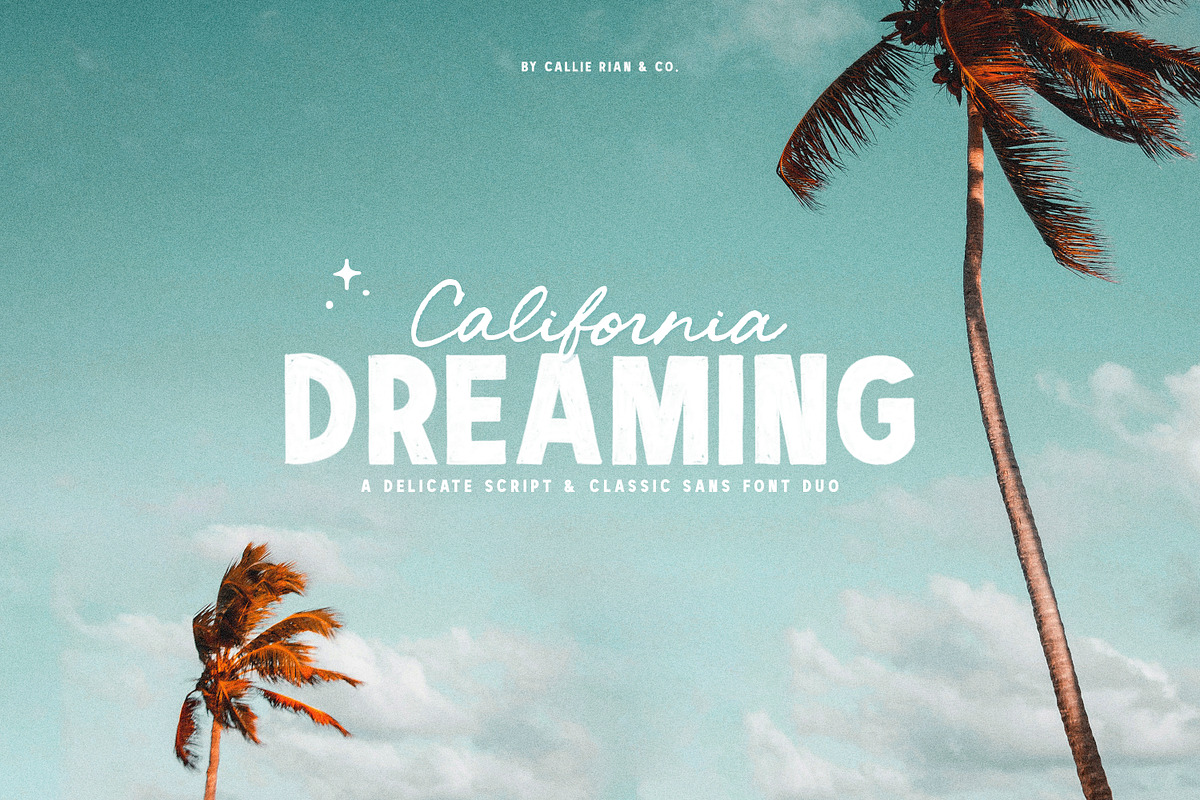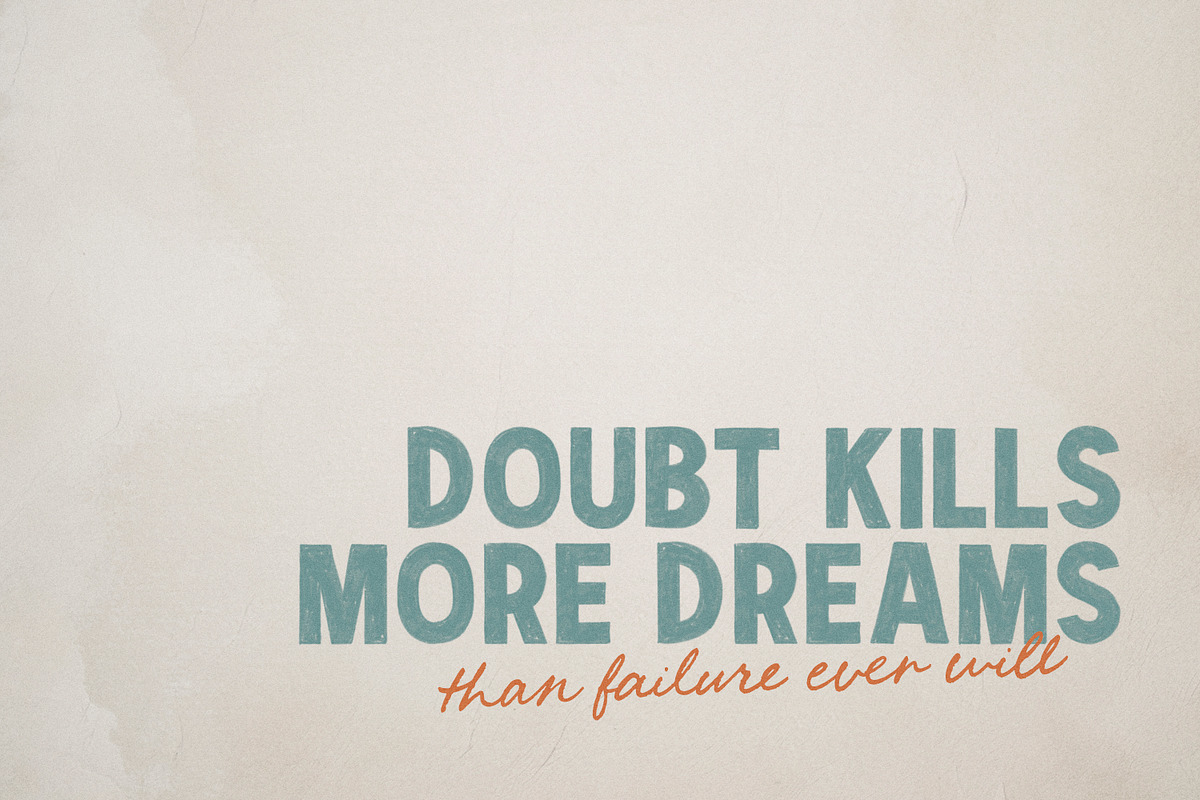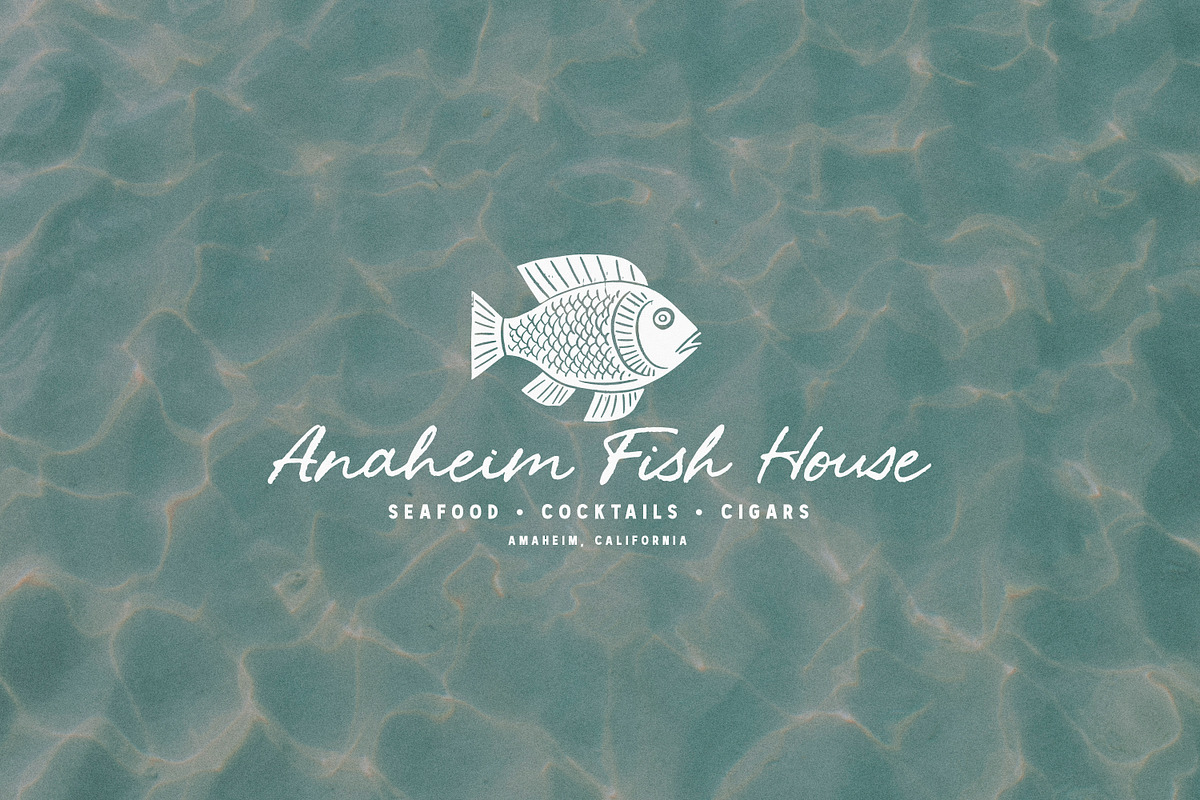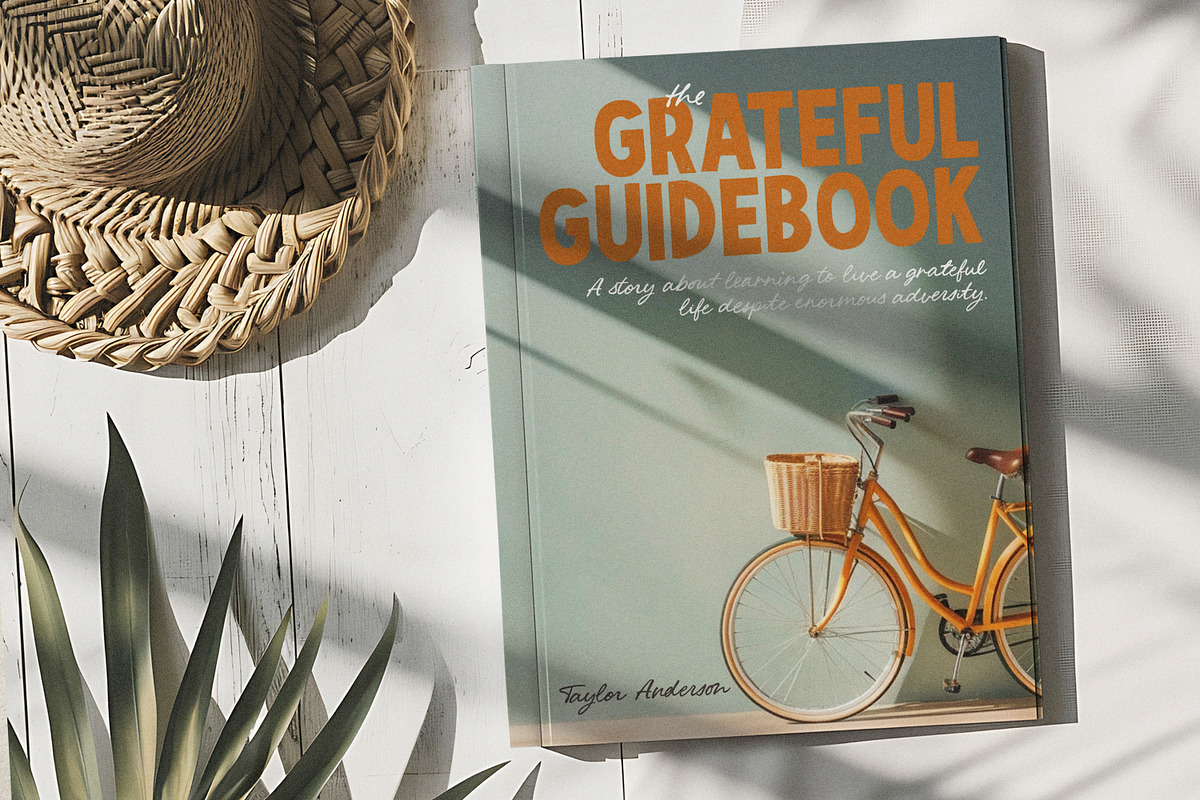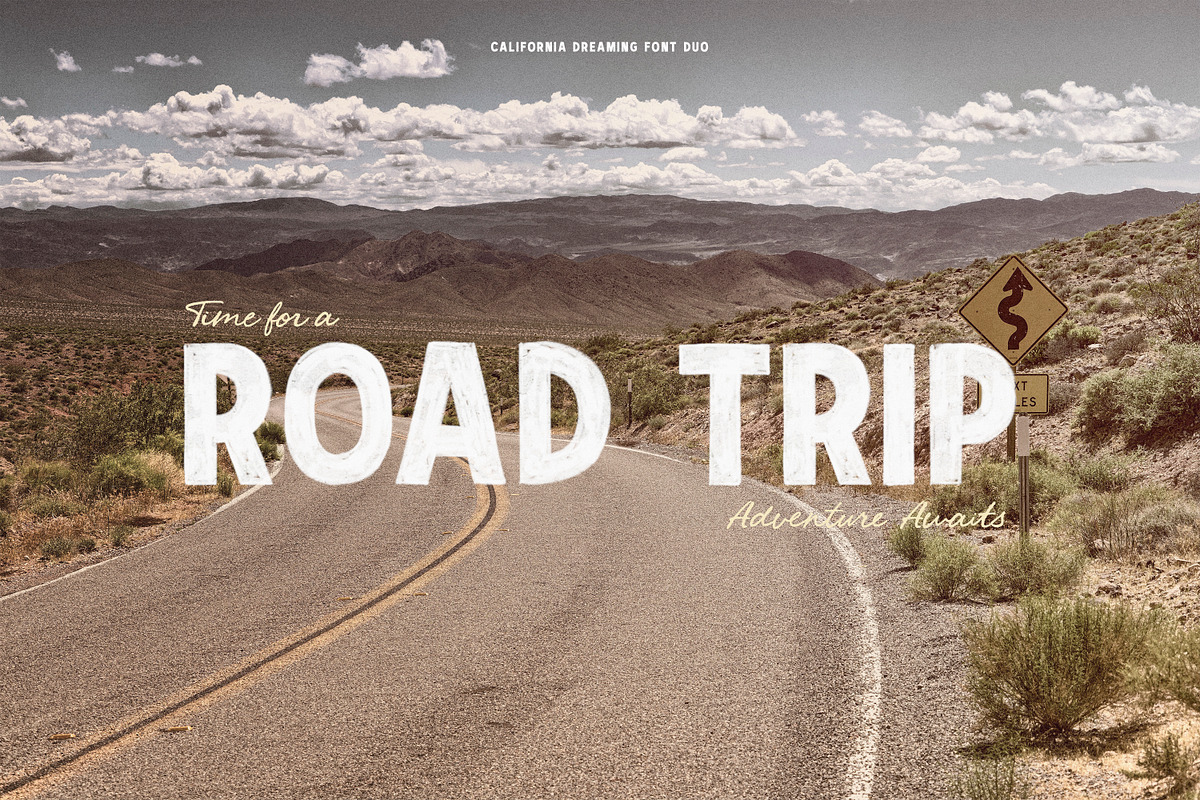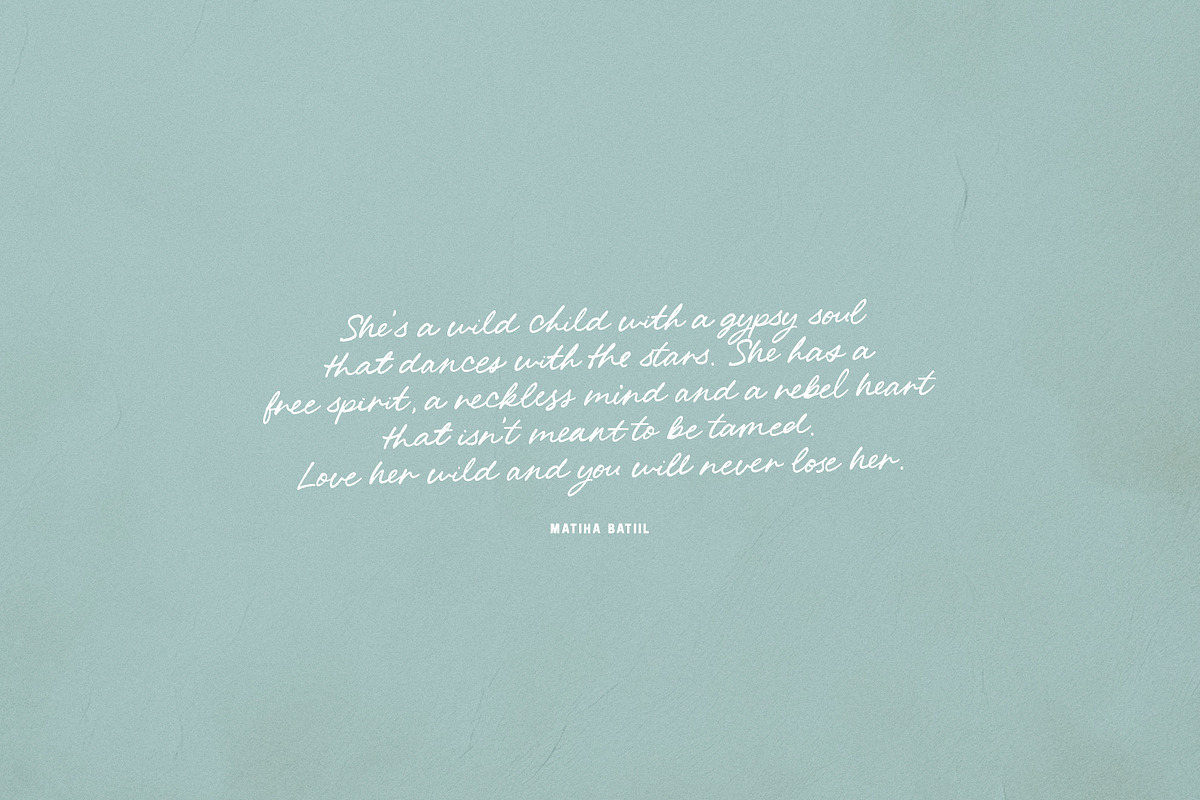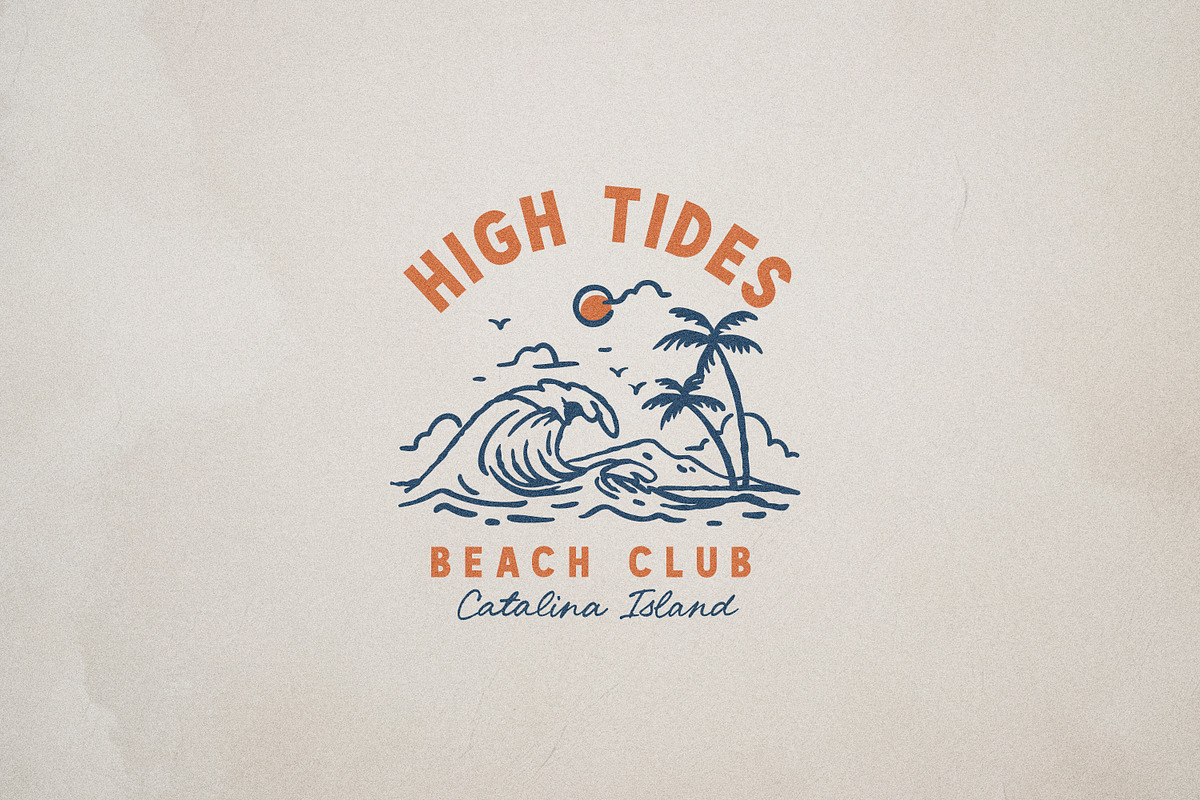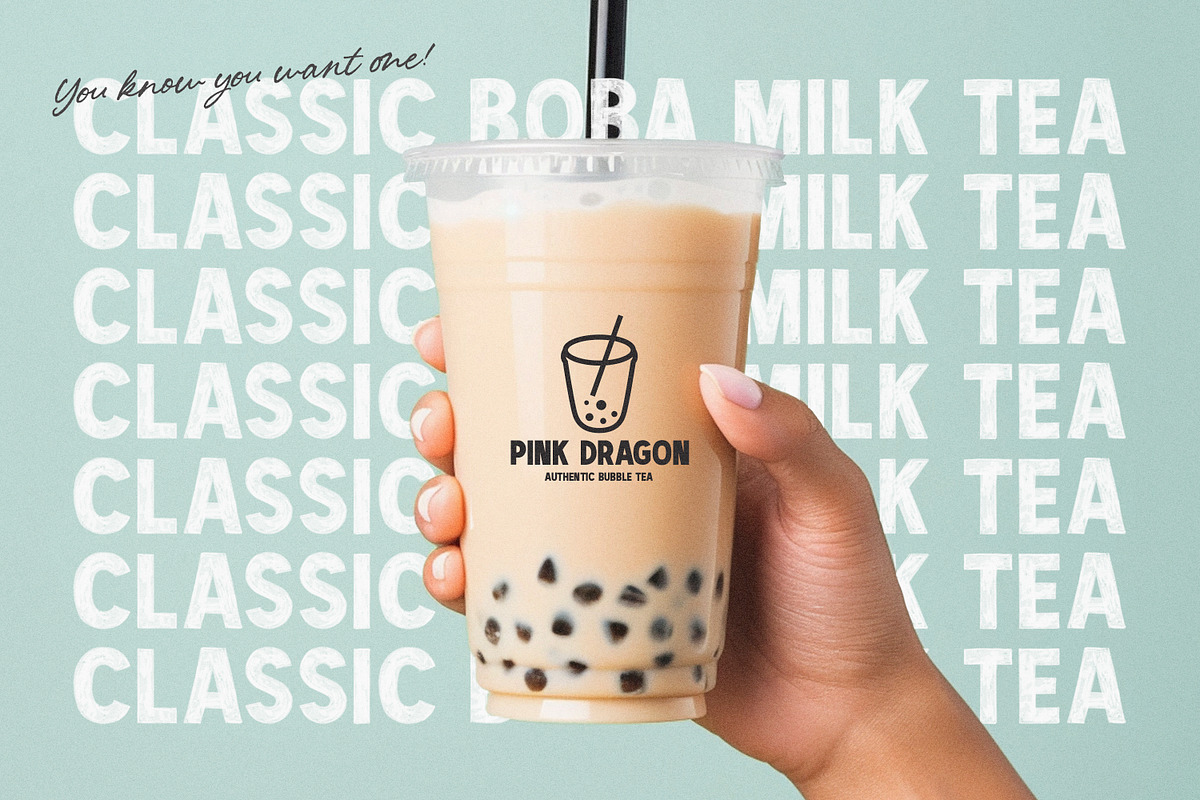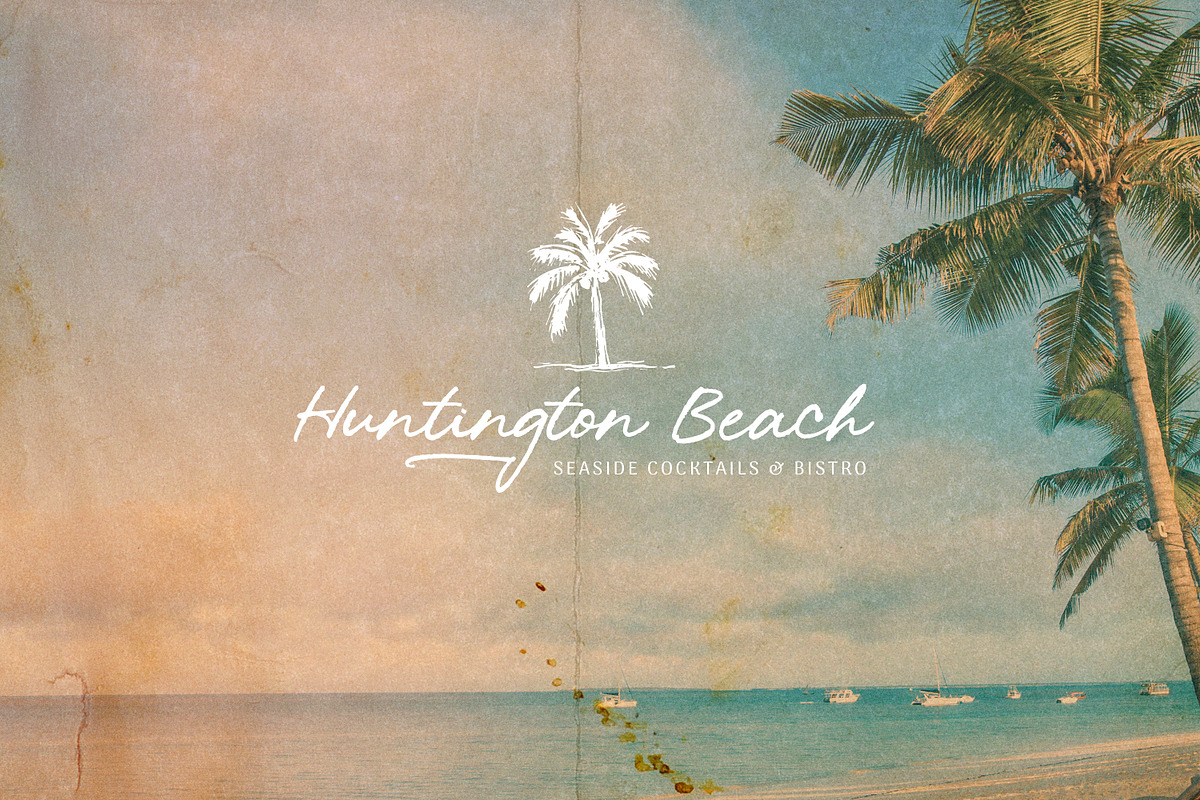
California Dreaming Script & Sans
California Dreaming – Font Duo Tangan Eksklusif dengan Sentuhan Vintage Modern
Ucapkan halo pada California Dreaming, font duo yang serasi dan sepenuhnya digambar tangan! Menggabungkan script bertekstur alami dan sans serif klasik (tersedia dalam 4 varian termasuk versi SVG yang penuh karakter), font ini siap mempercantik berbagai desain Anda. Mulai dari headline, tagline, sampul buku, kartu ucapan, postcard, produk, stiker, hingga konten media sosial—California Dreaming memberikan nuansa unik dan hangat dalam setiap proyek.
Font ini dibuat dengan cinta untuk semua kebutuhan desain modern yang ingin tetap terasa personal dan berjiwa bebas.
• California Dreaming Script (OTF): Font script halus dengan dukungan bahasa Eropa Barat, lengkap dengan 100+ alternates dan ligatur tulisan tangan.
• California Dreaming Sans (OTF): Sans serif klasik yang cocok dipasangkan dengan font script-nya.
• California Dreaming Sans Italic (OTF): Versi miring untuk sentuhan dinamis tambahan.
• California Dreaming Sans Rounded (OTF): Versi membulat yang memberikan kesan lembut dan bersahabat.
• California Dreaming Sans SVG (OTF): Font bitmap transparan dengan tekstur autentik untuk hasil desain yang lebih hidup.
• California Dreaming Script & SVG memiliki tekstur kasar dan tidak halus—tidak kompatibel dengan perangkat seperti Cricut atau Silhouette.